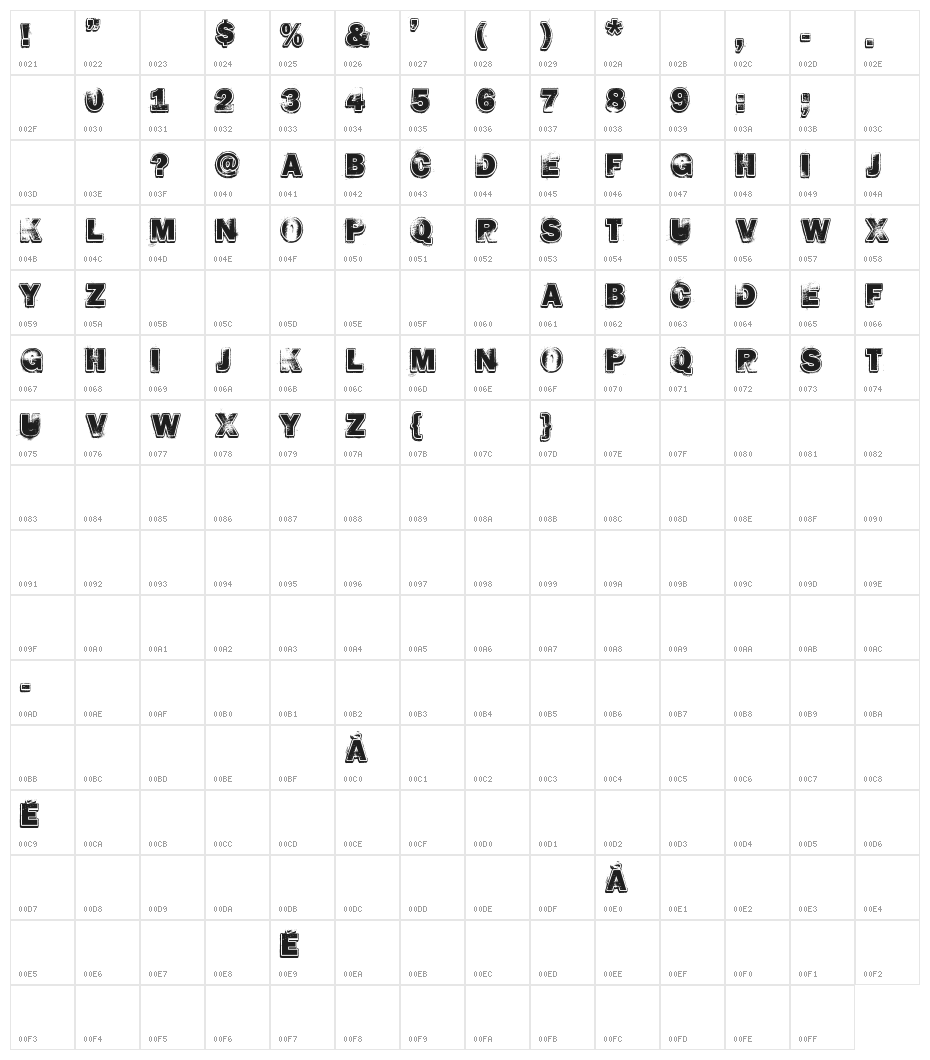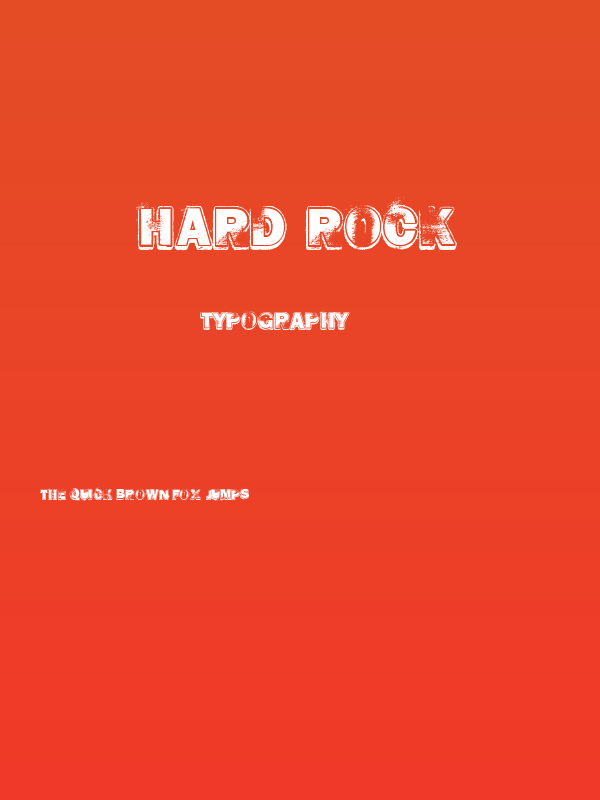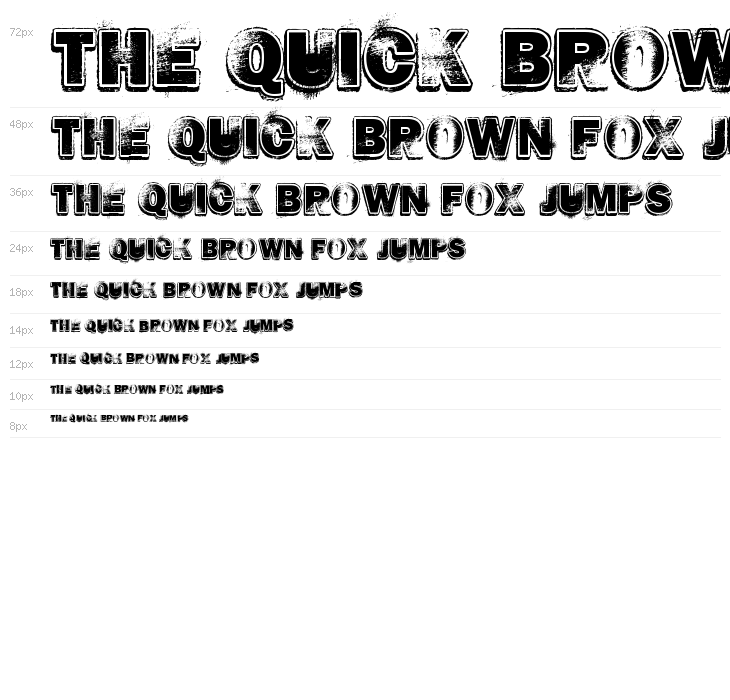
HARD ROCK Font
✎ Distorted Eroded
| Рекомендуемые проекты | Ideal for music album covers, posters, event flyers, and branding for edgy or alternative brands. |